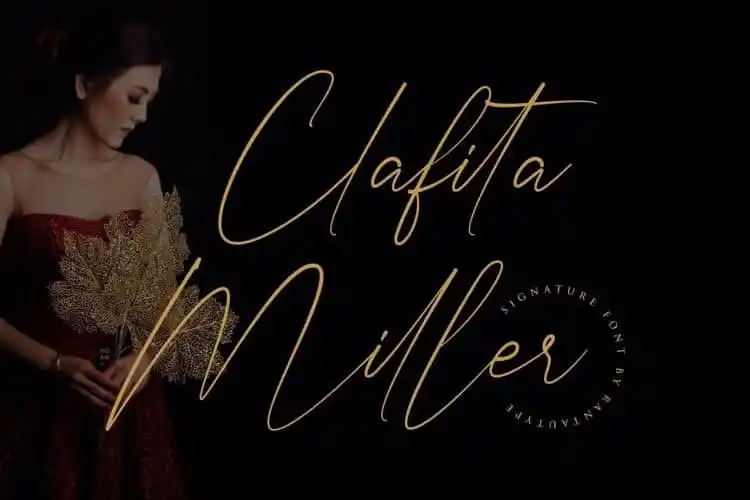
Clafita Miller Script Font – Download Grátis
A Clafita Miller Script Font é uma excelente opção para designers que buscam estilizar sua identidade visual com sofisticação e elegância. Feita pelo talentoso designer Rantautype, esta fonte atinge um equilíbrio perfeito entre modernidade e delicadeza, tornando-a ideial para marcas de produtos orgânicos como vinhos. Com uma aparência luxuosa, premium e fácil de ler, a Clafita Miller oferece a combinação perfeita de elegância e versatilidade. Ela é perfeitamente adaptável para uso em diversos projetos gráficos como logos, assinaturas, capas de livros e cartões de visita. Não importa qual seja o seu projeto, Clafita Miller está aqui para transformá-lo no nível mais alto possível. Seja você um designer dedicado ou uma marca buscando diferenciar sua marca através da escolha certa de fontes, a Clafita Miller é uma escolha inegável. Seu estilo único e versátil tornam-na uma opção ideal para aqueles que buscam estilizar suas criações com sofisticação e charme, garantindo um impacto visual imediato em qualquer projeto.